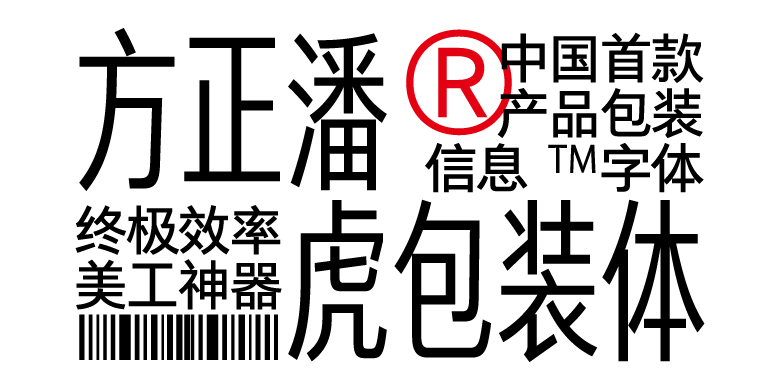
方正潘虎包装体家族
黑体、创意字体
在包装设计面临全球化与合规化双重挑战的今天,方正字库与潘虎设计实验室共同推出行业首款系统性字体解决方案。传统字体设计中,西文字符高度往往低于中文字符,导致包装设计师需要手动调整以满足“强制标示内容的文字、符号、数字的高度不得小于1.8mm”的强制要求。方正潘虎包装体创新性地采用统一字高标准,不仅确保中文字符、西文字符及关键符号均达到规范要求,更通过5档精细字重与6级灵活字宽的精准组合,为各类包装设计提供30款完美适配的字体方案。
在细节处理上,这套字体展现出惊人的匠心:竖钩的平势处理赋予文字稳重的气质,极简的人字头设计提升小字号的辨识度,科学的负空间调节有效避免印刷粘连。为满足全球市场需求,字体配备完整的字符集,涵盖拉丁文、西里尔文、希腊文等主要语系,使出口包装的多语言标注不再成为设计障碍。
这不仅是一套字体,更是一个完整的包装设计生态系统。配套开发的Adobe Illustrator智能排版插件将设计效率提升到全新高度,包括智能字号调节、一键生成条形码与调用包装场景特殊符号库等功能。方正潘虎包装体正在重新定义包装设计的标准,助力品牌在全球化竞争中赢得先机。